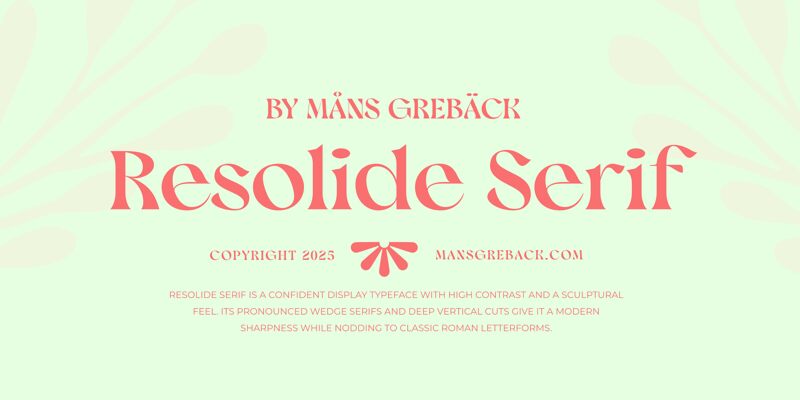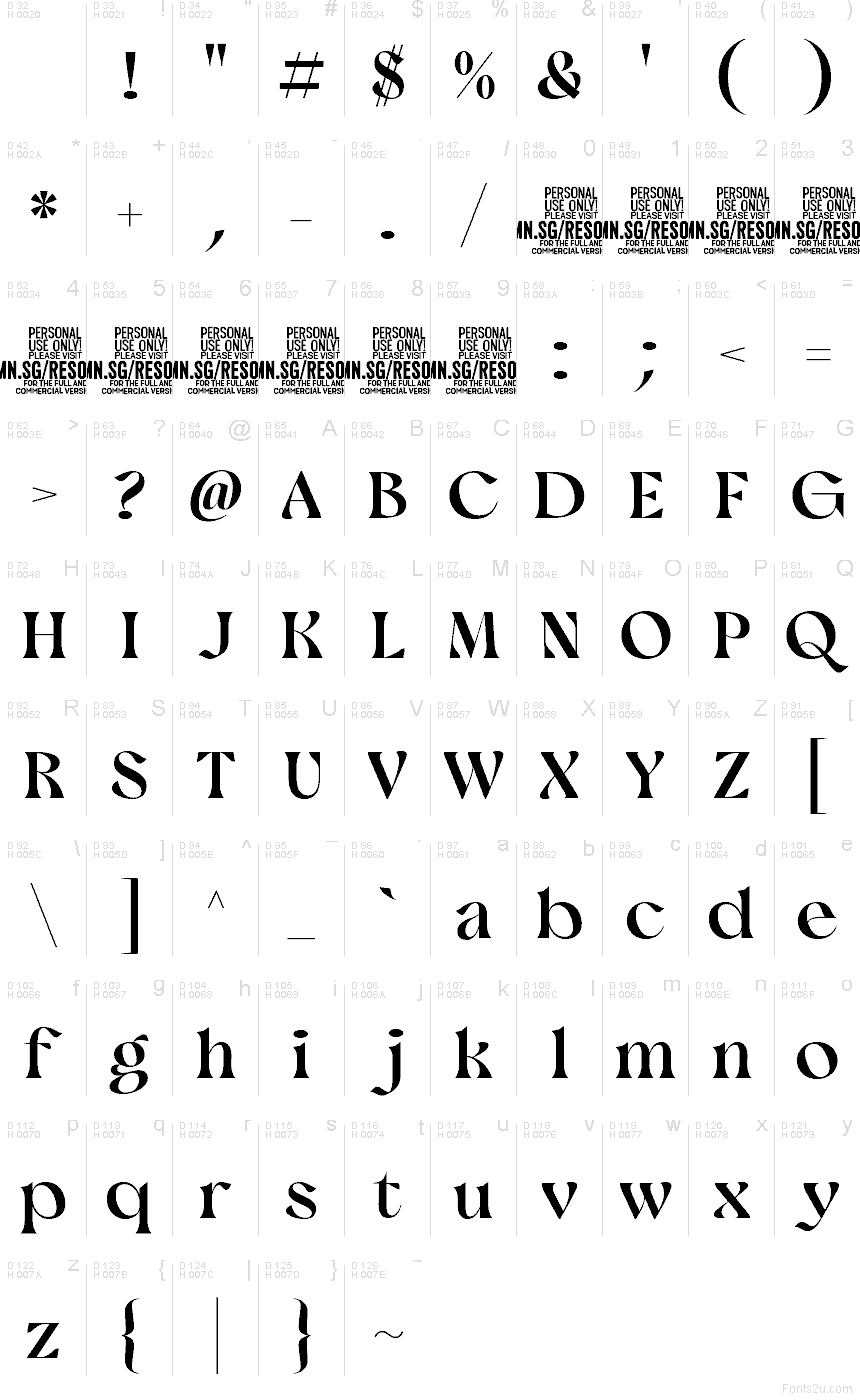
Resolide Serif PERSONAL USE Regular
Resolide Serif di Mans Greback AB è un font serif moderno, gratuito e ad alto contrasto, dal tono fashion e con un tratto leggermente teatrale. Le lettere uniscono curve scolpite e ampie a punte affilate, rendendo questo carattere elegante prima che decorativo.
È ideale per testate editoriali, packaging di boutique, branding nel settore beauty, copertine di libri e titoli dove poche parole devono trasmettere un ritmo misurato e stilizzato. Essendo un font gratuito, è perfetto anche per monogrammi e titoli brevi, poiché le curve drammatiche e i dettagli affusolati delle grazie conferiscono una presenza sofisticata anche a testi molto brevi.